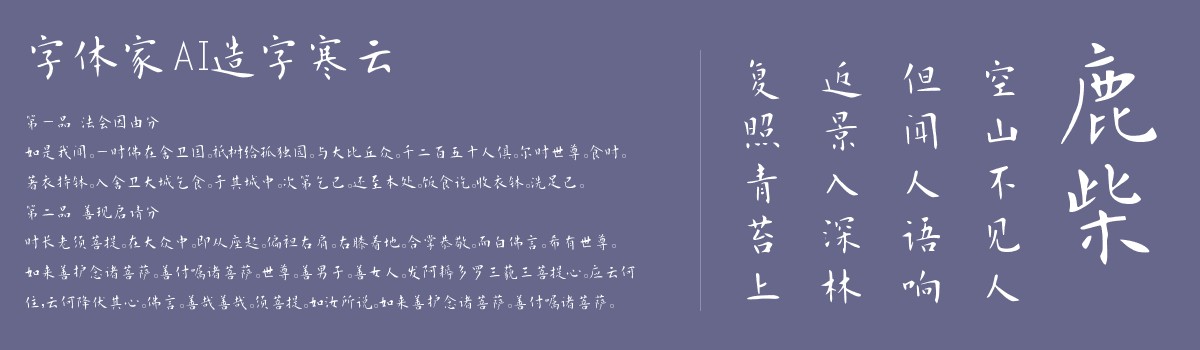
字体家AI造字寒云
字体家AI造字寒云是一款由字体家AI神笔造字生成的艺术字体,此字体似毛笔行云流水般书写,线条流畅温润,无生硬棱角。起笔收笔带自然晕染感,如墨在宣纸上轻缓晕开,提按间有细微粗细变化,横画舒展如轻云拂过,竖画挺拔似竹节含韧,撇捺末端微扬如羽翼轻展。结构均衡端庄,重心沉稳却不失灵动,笔画间偶有若隐若现的牵丝,似山间薄雾缠绕,整体如冬日寒云般清逸雅致,柔中带骨,既有手写的温度,又具文人的书卷气。适合用于一些广告标题、平面文案、海报标题、网页广告用字的编辑。